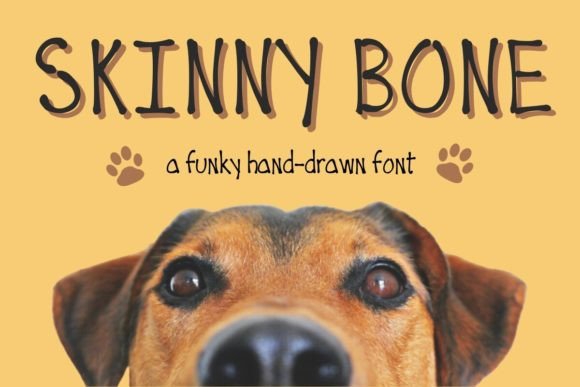
Skinny Bone
適切なデザイン要素を見つけるのは難しい場合がありますが、Skinny Boneは作品を即座に引き立てる優れたコレクションを提供します。
POD(オンデマンド印刷)製品、結婚式の招待状、またはソーシャルメディアのグラフィックを作成している場合でも、Skinny Boneは理想的です。